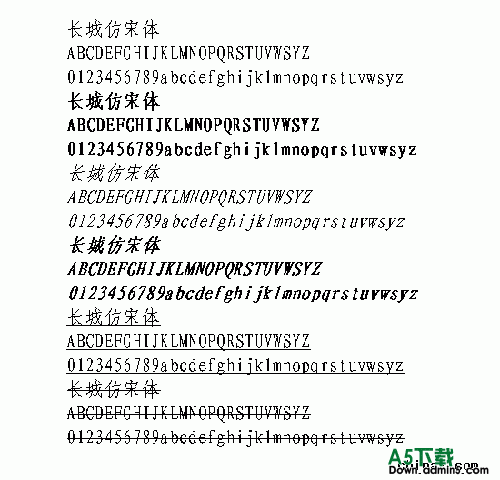
長(zhǎng)城仿宋體是一種較長(zhǎng)的仿宋字體,長(zhǎng)城仿宋體是主要用于工程制圖中的標(biāo)準(zhǔn)用字體,是專(zhuān)業(yè)性極強(qiáng)的中文漢字字體,易于書(shū)寫(xiě),規(guī)范美觀(guān),廣泛應(yīng)用于工程設(shè)計(jì)行業(yè)。